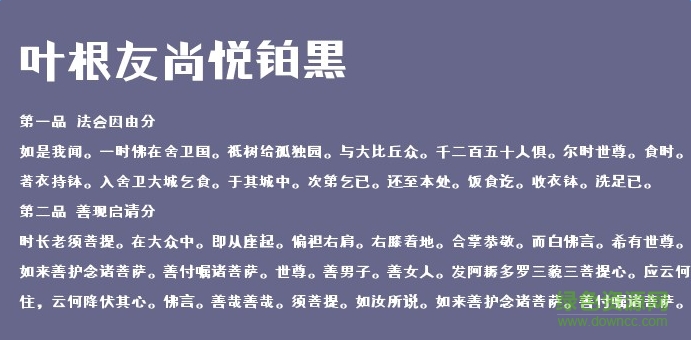
葉根友尚悅鉑黑字體
葉根友尚悅鉑黑是一款葉根友系列古典優(yōu)雅風(fēng)格字體軟件,字體筆畫粗黑,不拘不俗,整體效果十分端莊大方,喜歡這款字體就到綠色資源網(wǎng)下載體驗吧!
葉根友尚悅鉑黑字體介紹
葉根友尚悅鉑黑,歷史數(shù)年制作,近日完成內(nèi)測發(fā)布,這款字體在字形方面,體現(xiàn)出了剛勁有力量的時尚元素,同時也告訴大家一個小小的福利,用這個字體可以打出“biangbiang面”的“biang”字哦——
小編點評
該字體筆畫粗獷,每個字體所占空間一致,給人非常得體大方的感覺,非常的好看!喜歡就來下載使用吧!